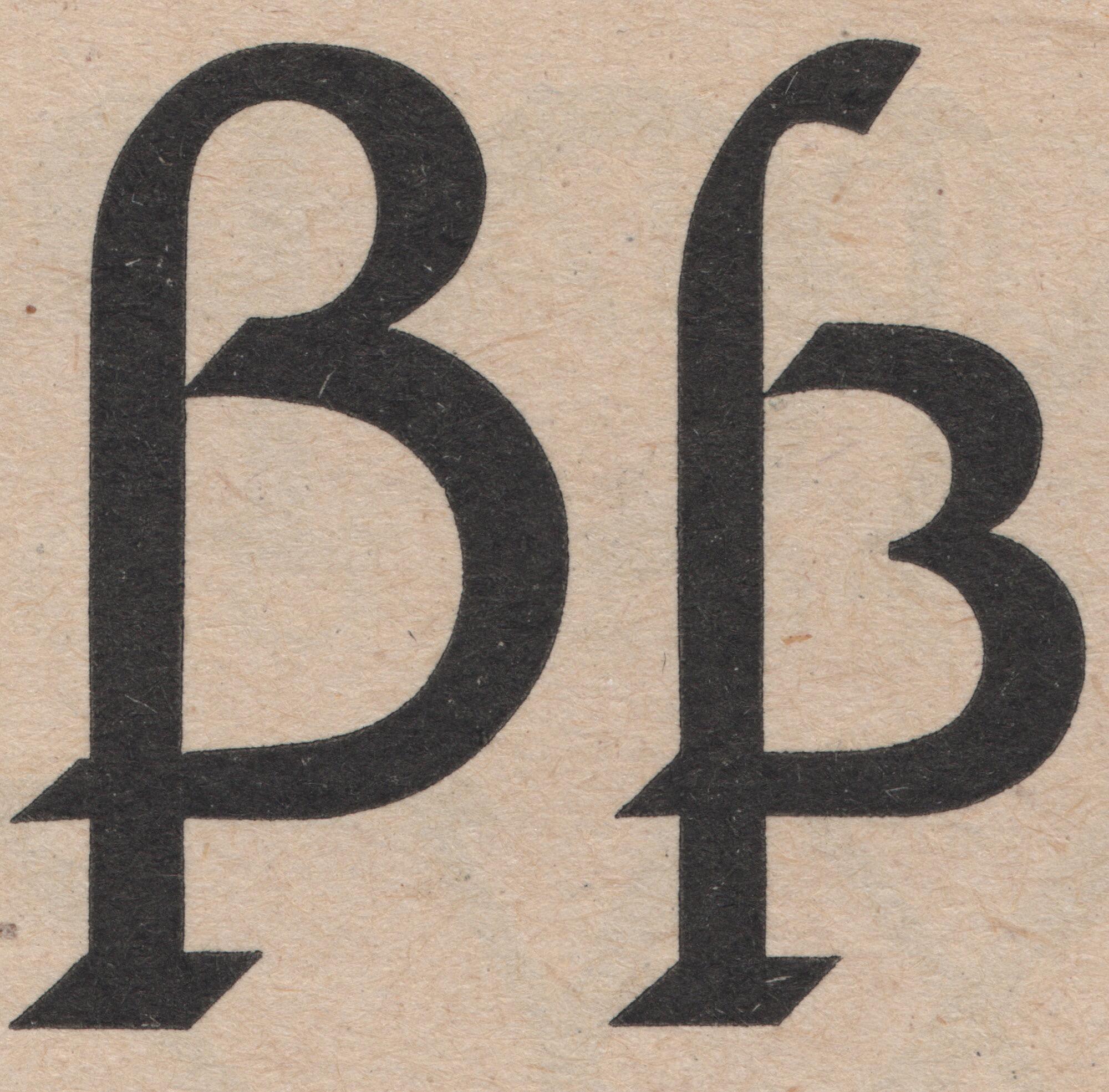
Font-Wiki: Ehmcke-Rustika
• 1914
• Serifen:
• serif
• Antiqua humanistisch
• Versaleszett:
• enthalten
Die Ehmcke-Rustika von Fritz Helmuth Ehmcke erschien 1914 bei der Schriftgießerei D. Stempel AG in einem Schnitt. Passend dazu erhältlich waren auch Initialen und Ornamente.
Eine moderne Adaption ist die Rustic von Dan Reynolds in fünf Strichstärken.